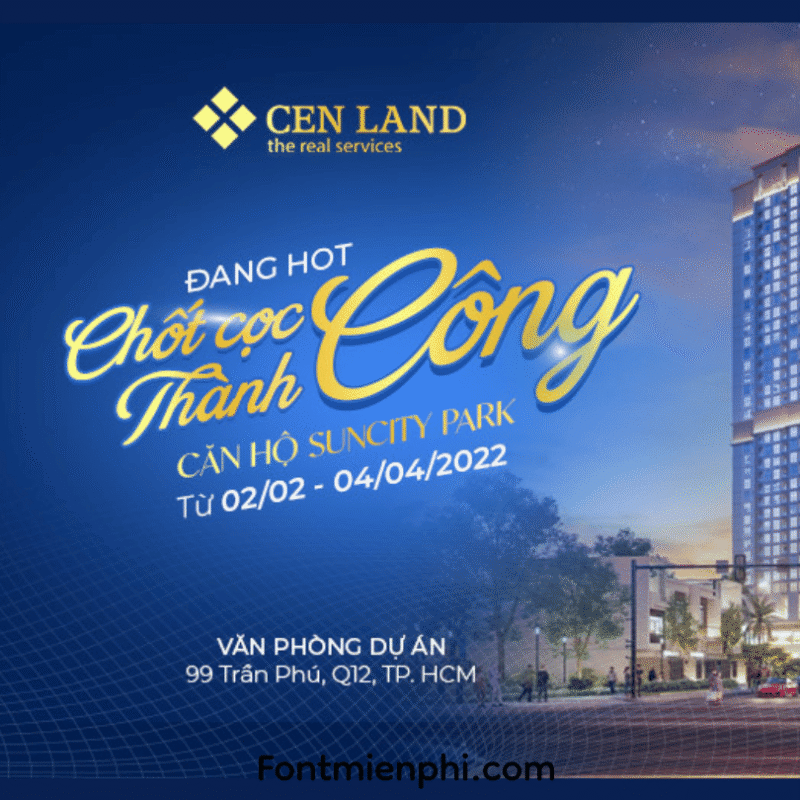
Font combo thiết kế bất động sản 1 , Sẳn hiệu ứng gradient trong file Ps
BỘ FONT COMBO THIẾT KẾ BẤT ĐỘNG SẢN 1 – CHUYÊN NGHIỆP & HIỆU ỨNG SẴN
Tổng quan bộ công cụ:
• Combo 3 font Việt hóa cao cấp (1 font chính + 2 font phụ) được phối màu sẵn
Thành phần chi tiết Font combo thiết kế bất động sản 1 , Sẳn hiệu ứng gradient trong file Ps
1️⃣ Font chính: Display bold – nét mạnh mẽ, dễ đọc từ xa
2️⃣ Font phụ 1: Clean sans-serif – cân bằng layout
3️⃣ Font phụ 2: Elegant script – điểm nhấn sang trọng
Tính năng đặc biệt:
✓ 5 mẫu gradient preset (vàng kim, xanh corporate, tông đất…)
Ứng dụng thực tế:
Backdrop hội thảo bất động sản
Banner quảng cáo dự án
Brochure, profile công ty
Social media template